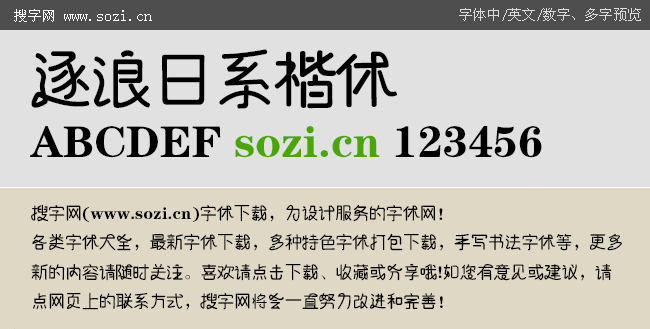
逐浪日系楷體
搜字網(wǎng)提供一款逐浪日系楷體中文字體下載,逐浪日系楷體是一款手寫風(fēng)格的個(gè)性化書法字體,該字體整體效果十分出色,適合應(yīng)用于廣告設(shè)計(jì)、名片設(shè)計(jì)、包裝印刷、產(chǎn)品設(shè)計(jì)等應(yīng)用。(逐浪字庫(kù)如需商用授權(quán),請(qǐng)聯(lián)系:0791-86161900 QQ:404655890)